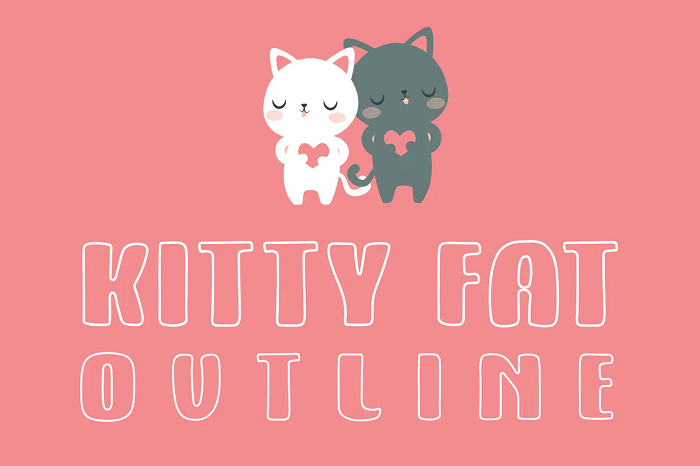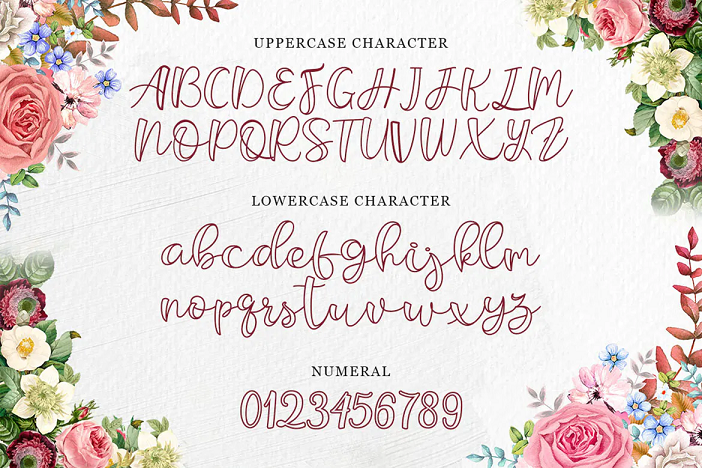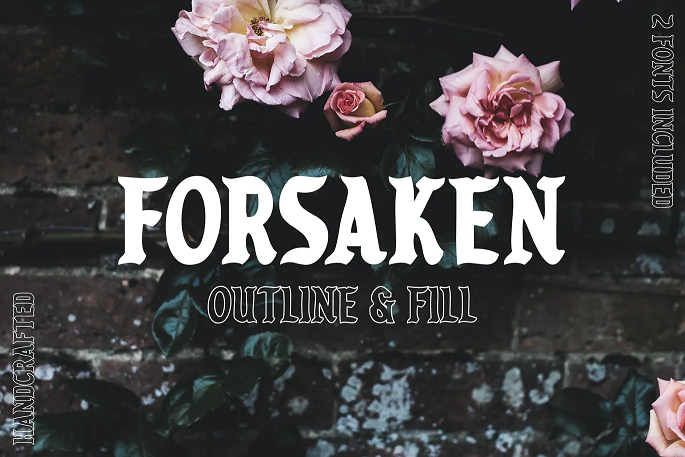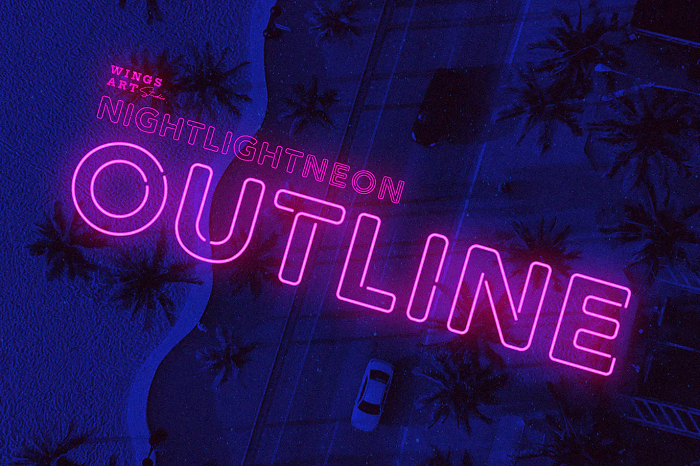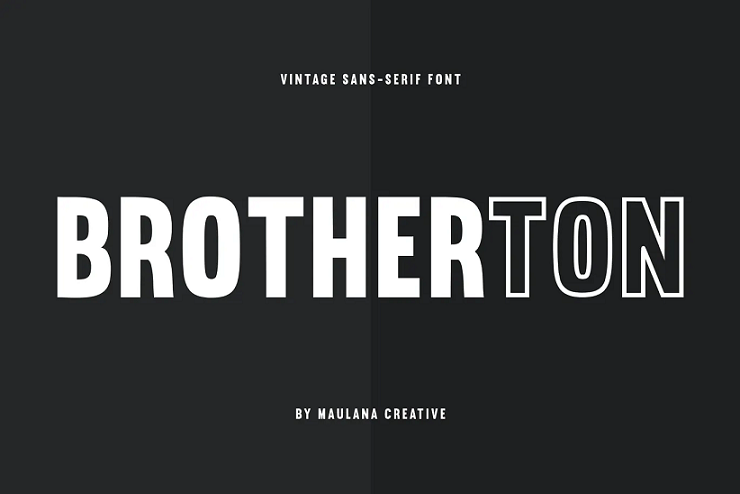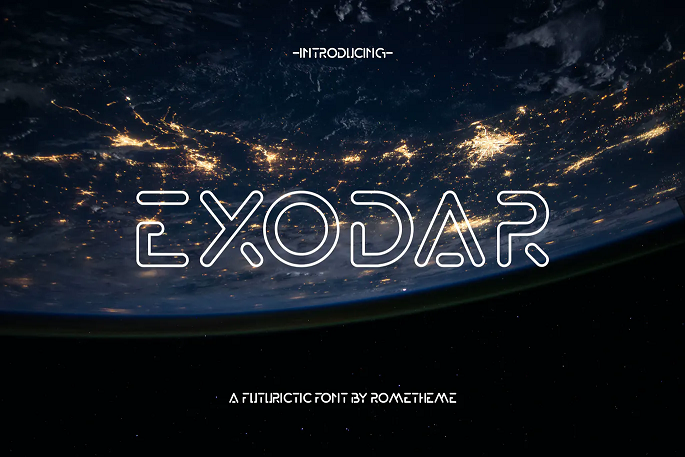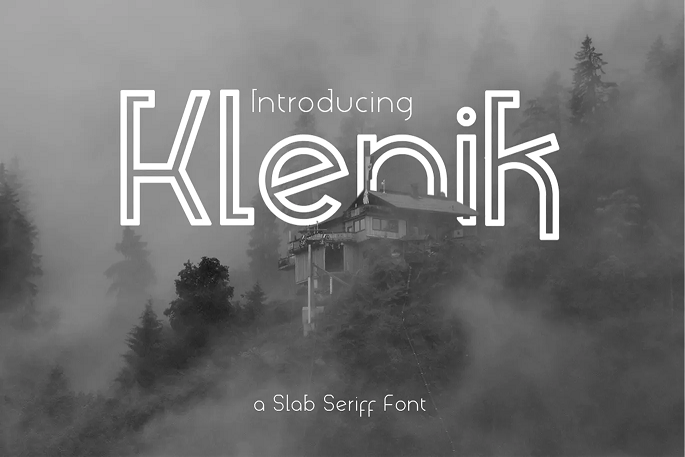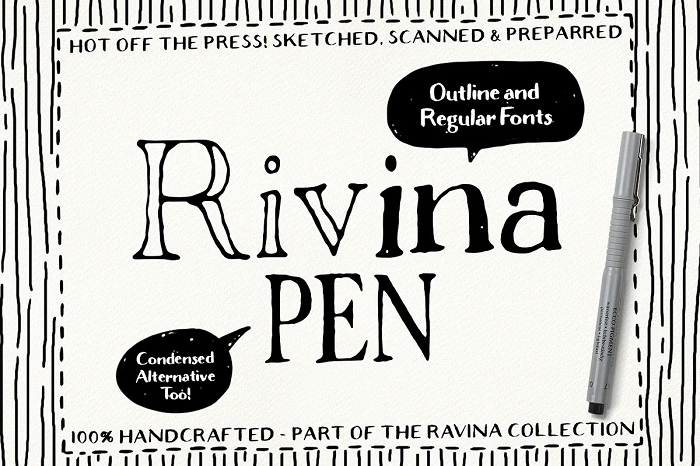
40 แบบอักษรและแบบอักษรสำหรับโครงร่างที่ดีที่สุดสำหรับปี 2023
เผยแพร่แล้ว: 2023-01-03ต้องการแบบอักษรที่มีสไตล์ที่จะช่วยให้คุณออกแบบให้ดูเป็นมืออาชีพและสร้างผลกระทบมากขึ้นหรือไม่? คุณต้องมีแบบอักษรเค้าร่าง
แบบอักษรเค้าร่างเหมาะสำหรับทุกการใช้งาน ตั้งแต่การออกแบบเว็บไปจนถึงโซเชียลมีเดียและอีกมากมาย อย่างไรก็ตาม การค้นหาฟอนต์ที่ดาวน์โหลดได้แบบง่ายๆ จะแสดงตัวเลือกต่างๆ นับพัน ดังนั้นการค้นหาฟอนต์ที่เหมาะสมจึงเป็นเรื่องที่ยากเกินเหตุ
นั่นเป็นเหตุผลที่เราสร้างรายการแบบอักษรโครงร่างที่ดีที่สุด 40 แบบในปี 2023 เพื่อให้คุณไม่ต้องเสียเวลาหลายชั่วโมงในการค้นหาแบบอักษรที่สมบูรณ์แบบสำหรับโครงการต่อไปของคุณ
แต่ก่อนที่เราจะเข้าเรื่อง เรามาดูกันก่อนว่าฟอนต์เค้าร่างคืออะไรและคุณใช้มันอย่างไร
Outline Font คืออะไร?
ฟอนต์เค้าร่างคือฟอนต์ที่ใช้โครงร่างทางเรขาคณิตของตัวอักษรและอักขระ ข้อได้เปรียบหลักของแบบอักษรเค้าร่างคือสามารถปรับขนาดได้ง่าย ดังนั้นจึงสามารถเพิ่มหรือลดขนาดได้โดยไม่ทำให้รูปร่างผิดเพี้ยน
ฟอนต์เค้าร่างเป็นตัวเลือกที่ยอดเยี่ยมหากคุณต้องการสร้างงานออกแบบระดับมืออาชีพที่จะดึงดูดความสนใจของผู้อ่านได้อย่างง่ายดาย
ไม่ว่าคุณกำลังสร้างโลโก้เว็บไซต์หรือจดหมายข่าวธุรกิจ ฟอนต์โครงร่างที่ดีจะช่วยปรับปรุงการออกแบบของคุณได้อย่างแท้จริง
แบบอักษรโครงร่างที่ดีที่สุด - ตัวเลือกอันดับต้น ๆ ของเรา
เพื่อไม่ให้เป็นการเสียเวลา เรามาดูรายการแบบอักษรโครงร่างที่ดีที่สุดกัน เริ่มจากความชอบส่วนตัวของเรา
01. แบบอักษร Minimalist ของ Exco Sans
Exco Sans เป็นฟอนต์โครงร่างที่ทันสมัยและเรียบง่ายเป็นพิเศษ ซึ่งสามารถให้สัมผัสของสไตล์ได้แม้กระทั่งงานออกแบบที่เรียบง่ายที่สุด ในแพ็คนี้จาก Envato Elements คุณสามารถใช้ฟอนต์โครงร่าง Exco Sans เป็นตัวเอียง เงา และฟอนต์เวอร์ชันปกติได้
ทำไม Exco Sans ถึงเป็นตัวเลือกอันดับต้น ๆ ของเรา
การออกแบบที่แตกต่างกัน 4 แบบทำให้คุณมีความยืดหยุ่นอย่างไร้ขีดจำกัดในการออกแบบสื่อที่เป็นข้อความ และยิ่งไปกว่านั้น การออกแบบที่เรียบง่ายแต่มีสไตล์ทำให้เหมาะสำหรับโครงการต่างๆ มากมาย
02. โครงร่าง Portico
Portico Outline เป็นแบบอักษรตัวหนาที่ทั้งเรียบง่ายและสะดุดตา แบบอักษรนี้ดูดีเมื่อใช้กับชื่อเรื่องและข้อความบรรทัดใหญ่ และเมื่อใช้ร่วมกับแบบอักษร Portico แบบปกติ
03. โครงร่างเบอร์ฟอร์ด
Burford Outline เป็นฟอนต์ที่ดูสะอาดตาและมีสไตล์ซึ่งได้รับแรงบันดาลใจจากฟอนต์และการออกแบบของยุโรป ตระกูลฟอนต์นี้มาพร้อมกับฟอนต์ที่แตกต่างกัน 13 แบบ รวมถึงตัวเลือกโครงร่าง และยังมีแพ็คพิเศษที่มีอักขระพื้นฐานบนแป้นพิมพ์ทั้งหมด
04. โครงร่างกิบสัน
Gibsons เป็นชุดฟอนต์ที่มีสไตล์และทันสมัย ซึ่งเหมาะอย่างยิ่งหากคุณต้องการสร้างงานออกแบบที่ให้ความรู้สึก 'ฮิปสเตอร์' อันเป็นเอกลักษณ์ ชุดฟอนต์มาพร้อมกับฟอนต์ตัวหนา กึ่งหนา และฟอนต์ร่างปกติให้คุณเลือก
05. วีเซีย ดี ยูโอ
Visia Duo เป็นชุดฟอนต์อเนกประสงค์ที่มีฟอนต์โครงร่าง 4 เวอร์ชันที่แตกต่างกัน ปกติ ตัวเอียง ตัวหนา และตัวเอียงหนา ชุดฟอนต์ยังมีฟอนต์เวอร์ชันที่ไม่ได้ร่างโครงร่างไว้ด้วย
06. แสงจันทร์
Moonlite เป็นแบบอักษรโครงร่างตัวหนาที่สมบูรณ์แบบสำหรับการสร้างชื่อเรื่องและบรรทัดข้อความให้โดดเด่น ชุดมาพร้อมกับฟอนต์เค้าร่างใน OTF/TTF/WOFF รวมถึงฟอนต์ทึบที่เข้าชุดกัน
07. แบบอักษร Melburch
Melburch Outline เป็นฟอนต์เค้าร่างที่ได้รับแรงบันดาลใจจากวินเทจ เหมาะอย่างยิ่งสำหรับการสร้างงานออกแบบย้อนยุค ชุดฟอนต์เค้าร่างนี้มาพร้อมกับฟอนต์แบบปกติและแบบเอียง
08. โครงร่าง Nostromo
Nostromo เป็นแบบอักษรแห่งอนาคตที่ได้รับแรงบันดาลใจจากนิยายวิทยาศาสตร์ เหมาะอย่างยิ่งสำหรับบริษัทด้านเกมหรือเทคโนโลยี ชุดประกอบด้วยฟอนต์เวอร์ชันปกติและเวอร์ชันร่าง และยังมีเครื่องหมายวรรคตอนเพื่อให้เหมาะกับภาษายุโรปที่หลากหลาย
09. เค้าโครงหน้า
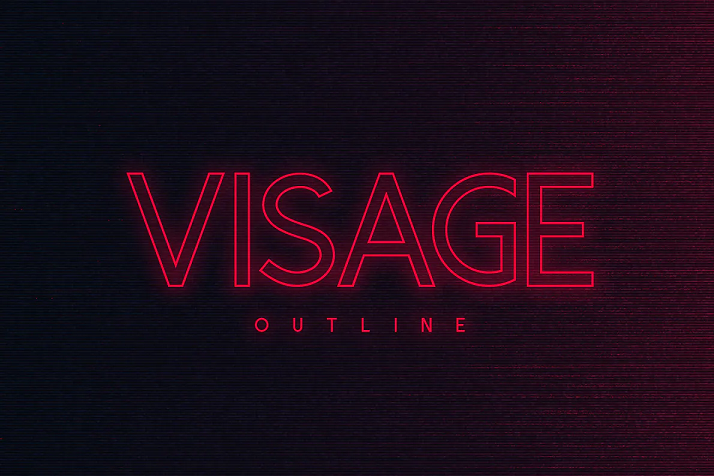
โครงร่าง Visage เป็นฟอนต์โครงร่างที่เรียบง่ายแต่ดึงดูดสายตาซึ่งดูดีเนื่องจากเป็นส่วนหนึ่งของการออกแบบที่ได้รับแรงบันดาลใจจากไฟนีออน นี่คือฟอนต์ตัวพิมพ์ใหญ่ และแพ็คนี้ยังมีเครื่องหมายวรรคตอนและตัวเลขทั่วไปอีกด้วย
10. อิสรภาพตลอดกาล
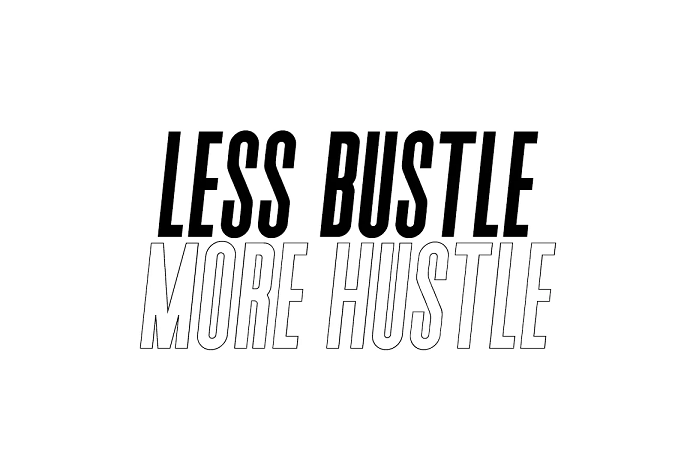
Forever Freedom เป็นตระกูลฟอนต์สมัยใหม่ที่โดดเด่นสมบูรณ์แบบสำหรับการออกแบบที่โดดเด่น ตระกูลฟอนต์ monoscaped นี้มีสองตัวเลือก แบบปกติและตัวเอียง
11. โครงร่าง Hikou
Hikou Outline เป็นอีกตัวเลือกที่ดีหากคุณกำลังมองหาแบบอักษรนีออนที่ยอดเยี่ยม แบบอักษรนี้มีตัวพิมพ์ใหญ่ ตัวเลข และเครื่องหมายวรรคตอน และเหมาะสำหรับชื่อเรื่องและเนื้อหาโซเชียลมีเดีย
40. Oles ans
Olesans เป็นแบบอักษรโครงร่างที่ทันสมัยซึ่งเหมาะสำหรับเนื้อหาและโลโก้ส่งเสริมการขาย แบบอักษรมาพร้อมกับตัวพิมพ์ใหญ่ ตัวพิมพ์เล็ก และอักขระพิเศษ